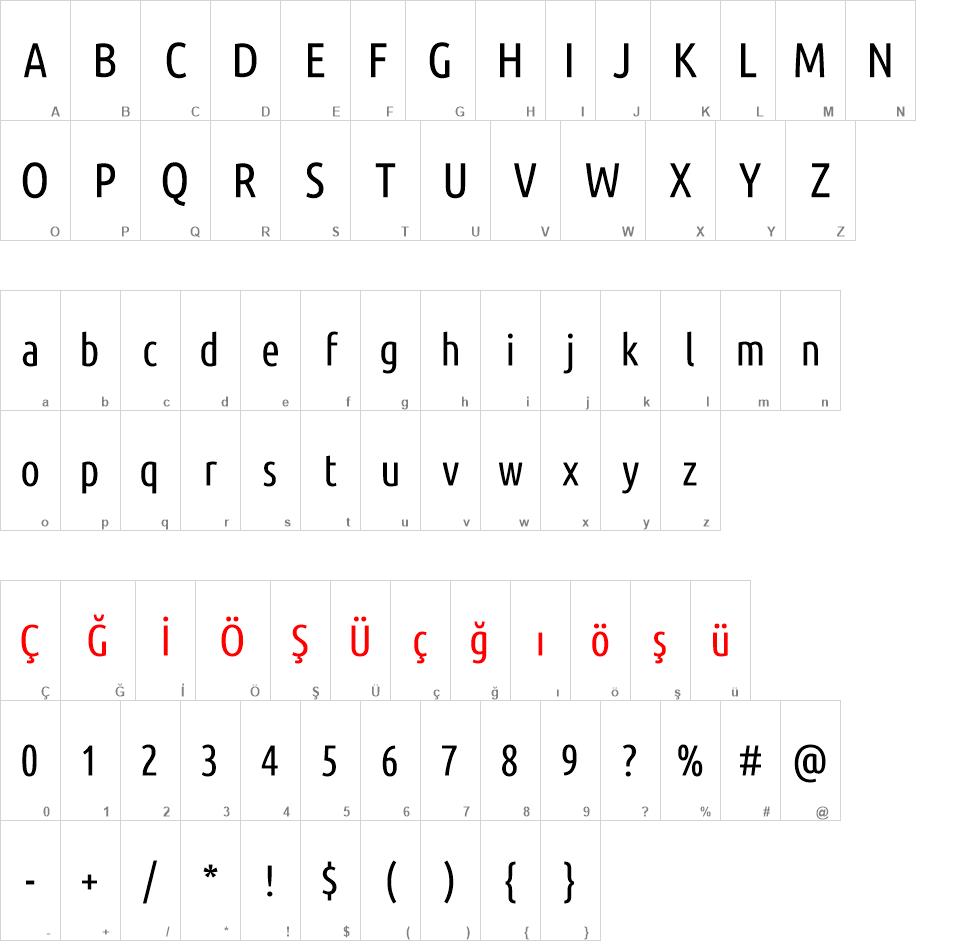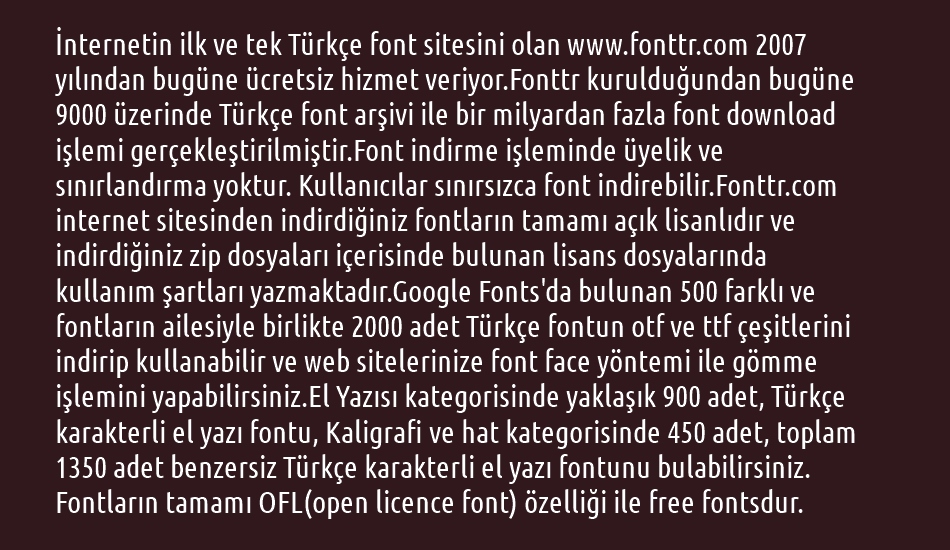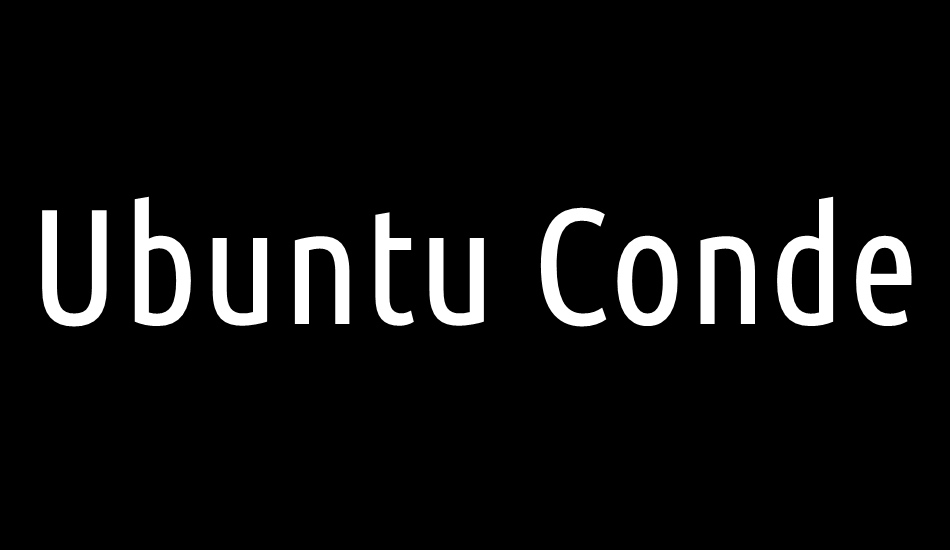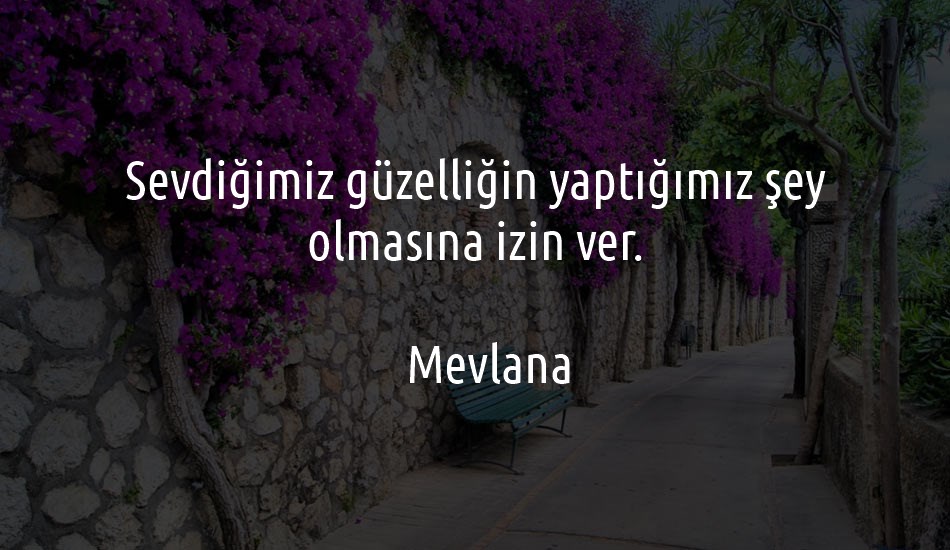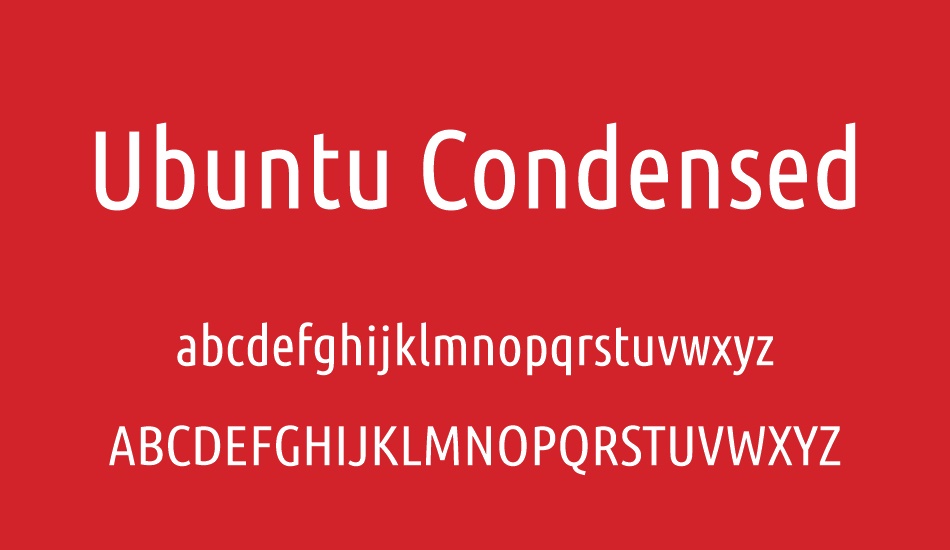
Ubuntu Condensed font
Ubuntu Condensed Yazı Tipi Ailesi, 2010-2011 yılları arasında yeni libre / açık fontlarla eşleşen bir dizi kümesidir. geliştirme adına, Canonical Ltd. tarafından geniş Ücretsiz Yazılım toplum ve Ubuntu projesini finanse ediliyor. Teknik font tasarımı çalışmaları ve uygulaması Dalton Maag tarafından üstlenilmektedir.
Yeni Ubuntu Condensed font Yazı Tipi Ailesi görülecek Ubuntu kişiliğini yapabilmek için başlatıldı ve her menü, düğme ve iletişim hissedildi. Yazı tipi sans-serif, OpenType özelliklerini kullanır ve manuel masaüstü ve mobil bilgisayar ekranlarında netlik için ima olmasıdır.
Ubuntu Yazı Ailesi kapsamı her kullanıcının kendi seçtikleri dilde kendi yazılımı kullanmak mümkün olmalıdır belirten Ubuntu'nun felsefesi ile uyum halinde dünyanın çeşitli Ubuntu kullanıcıları tarafından kullanılan tüm dilleri kapsar. Dolayısıyla Ubuntu Yazı Tipi Ailesi projesi daha birçok yazılı dili kapsayacak şekilde genişletilecek.